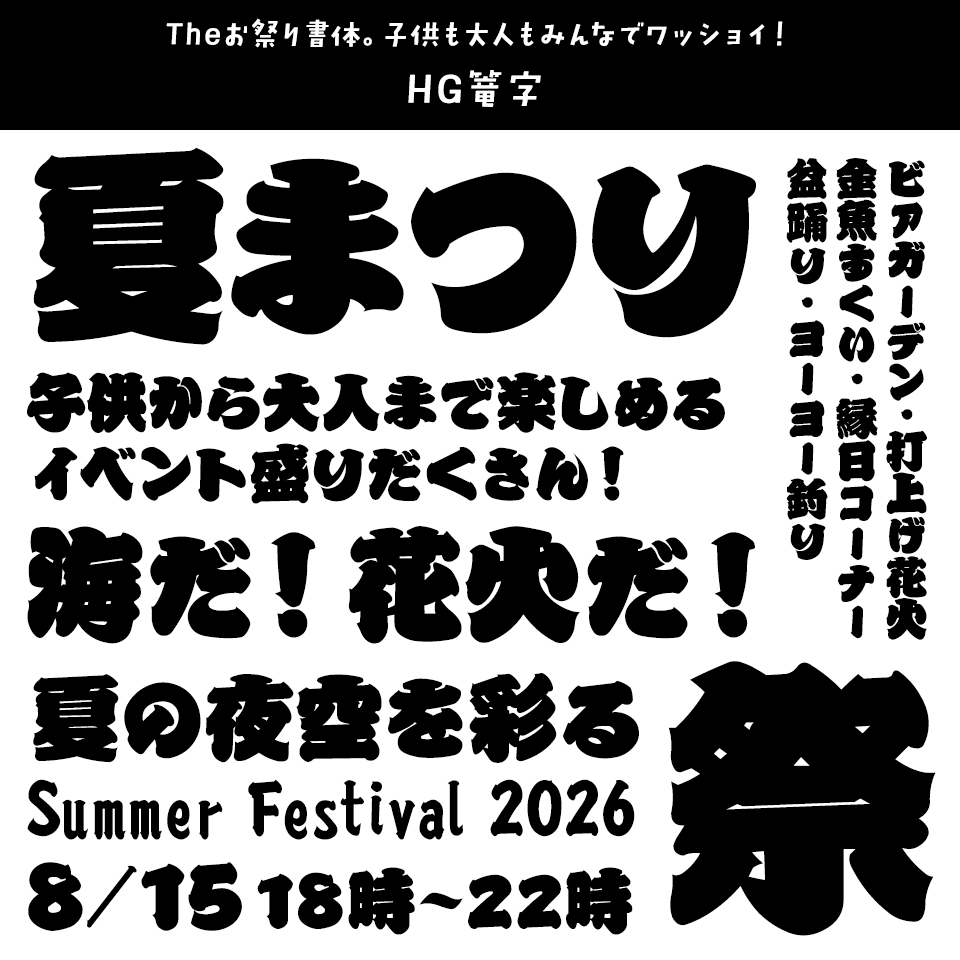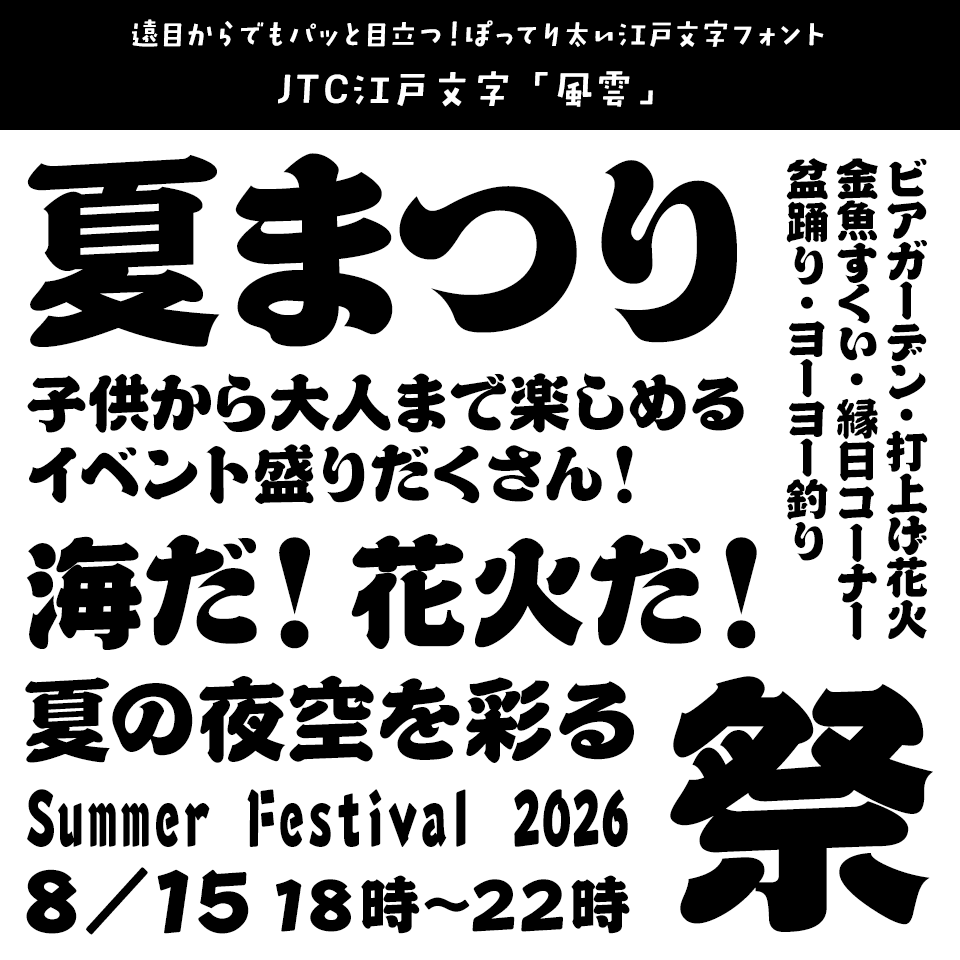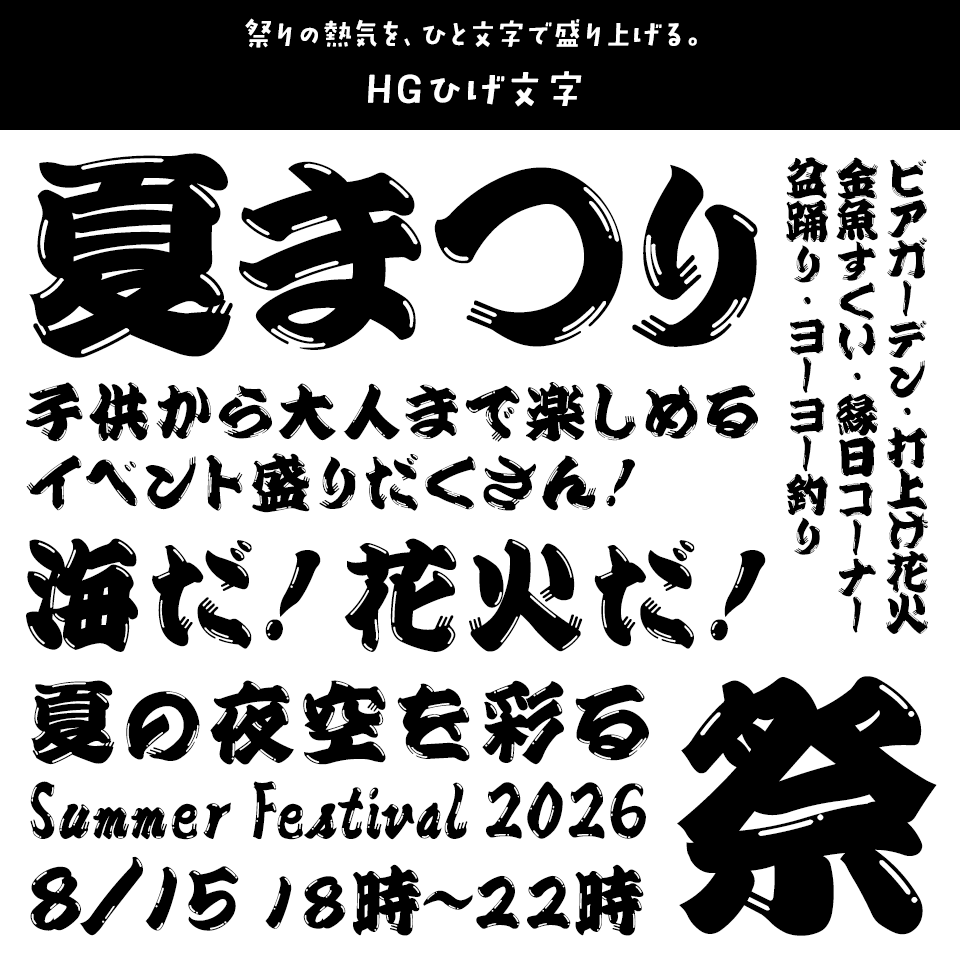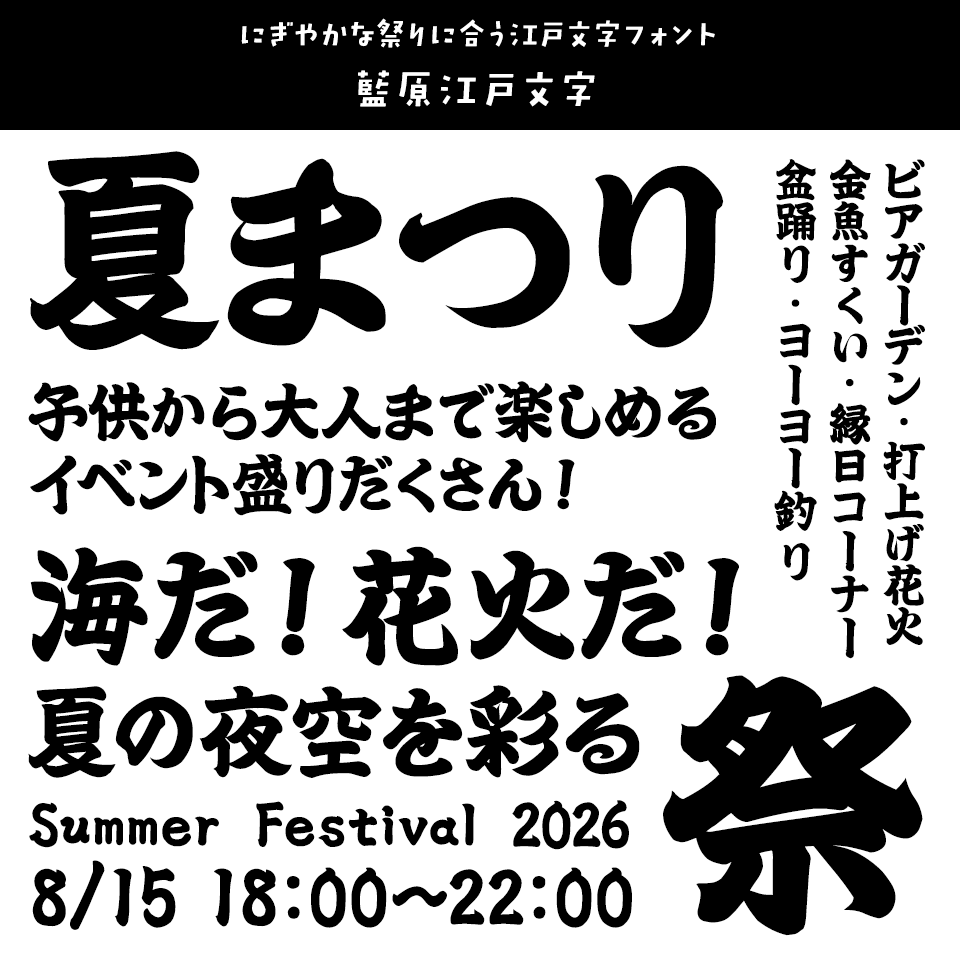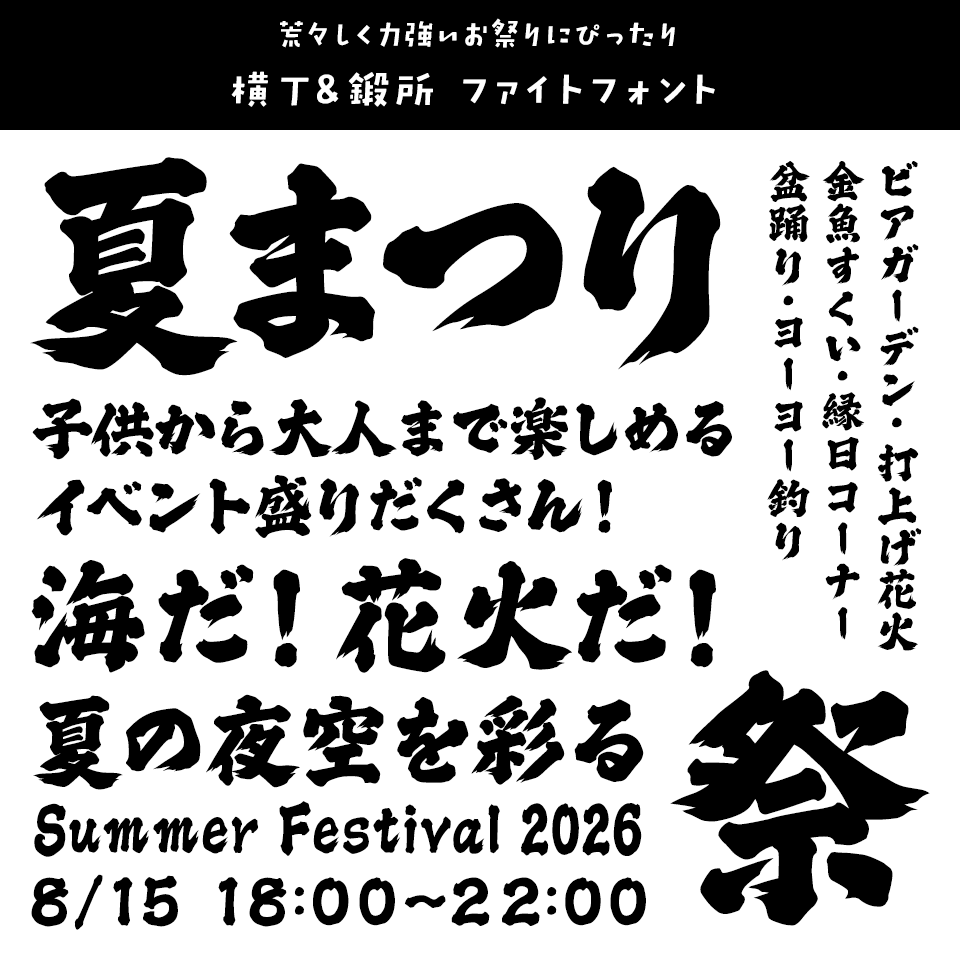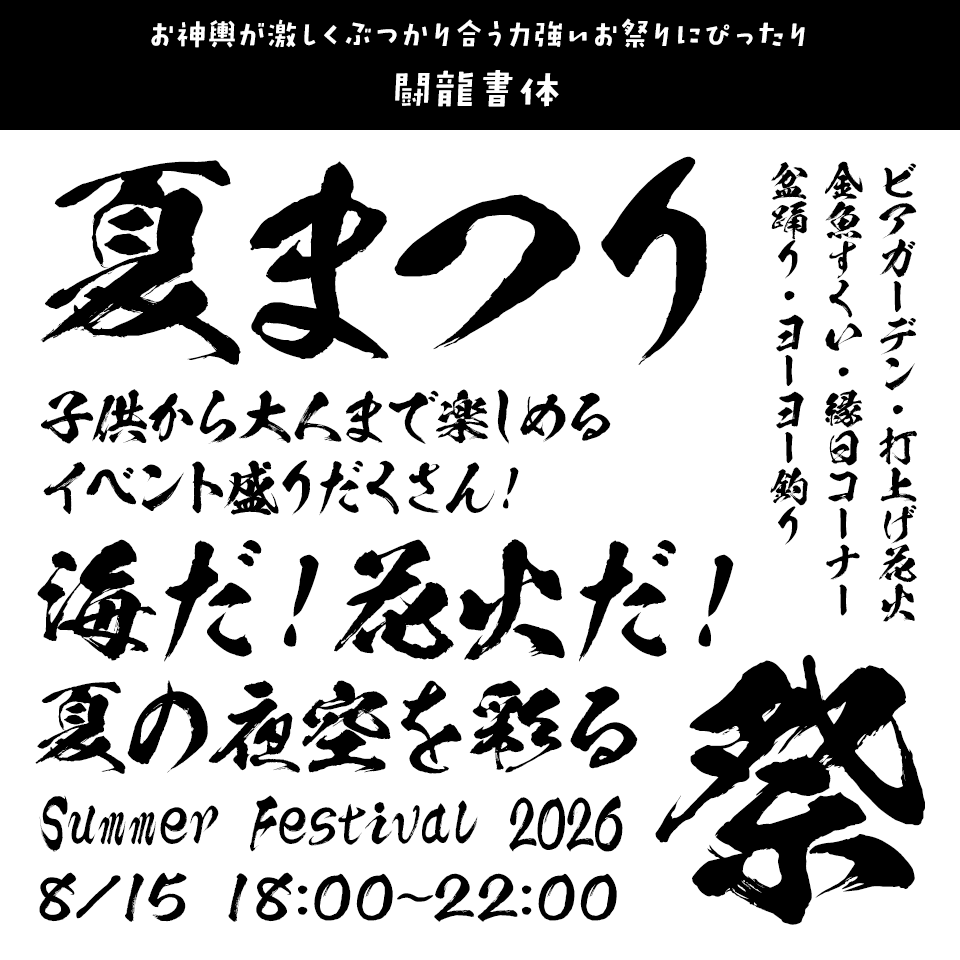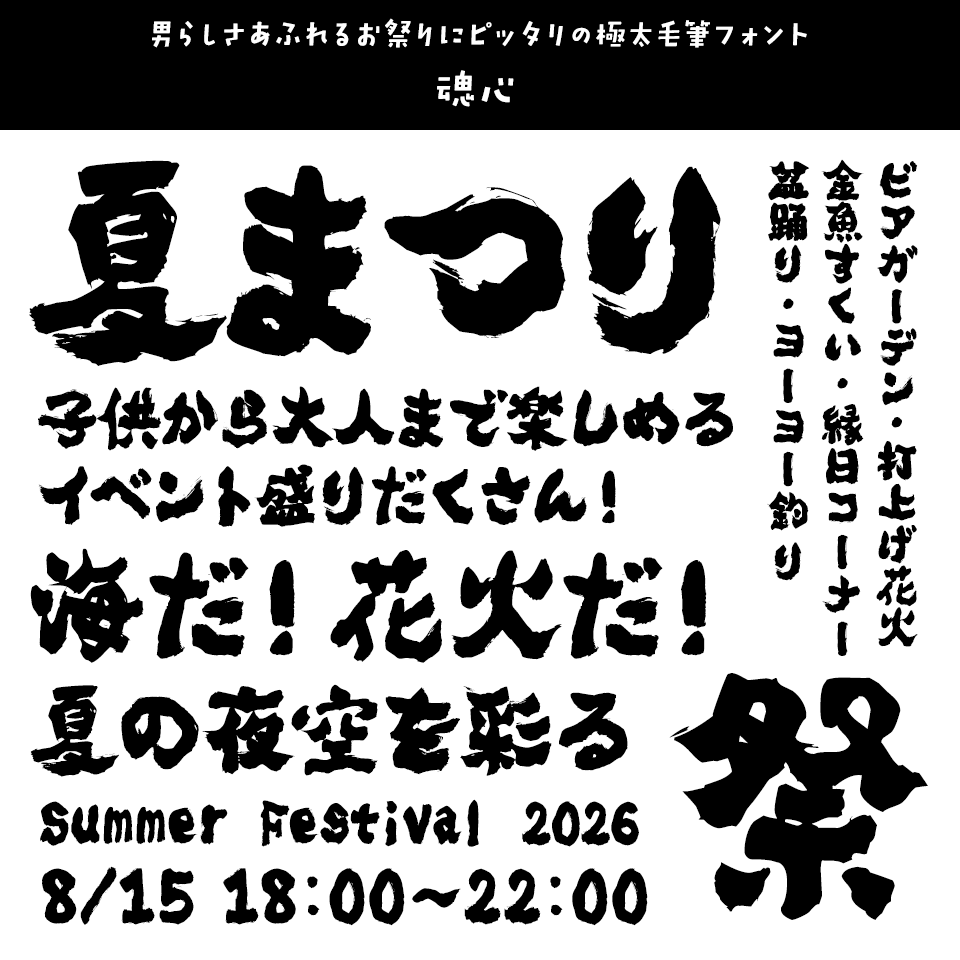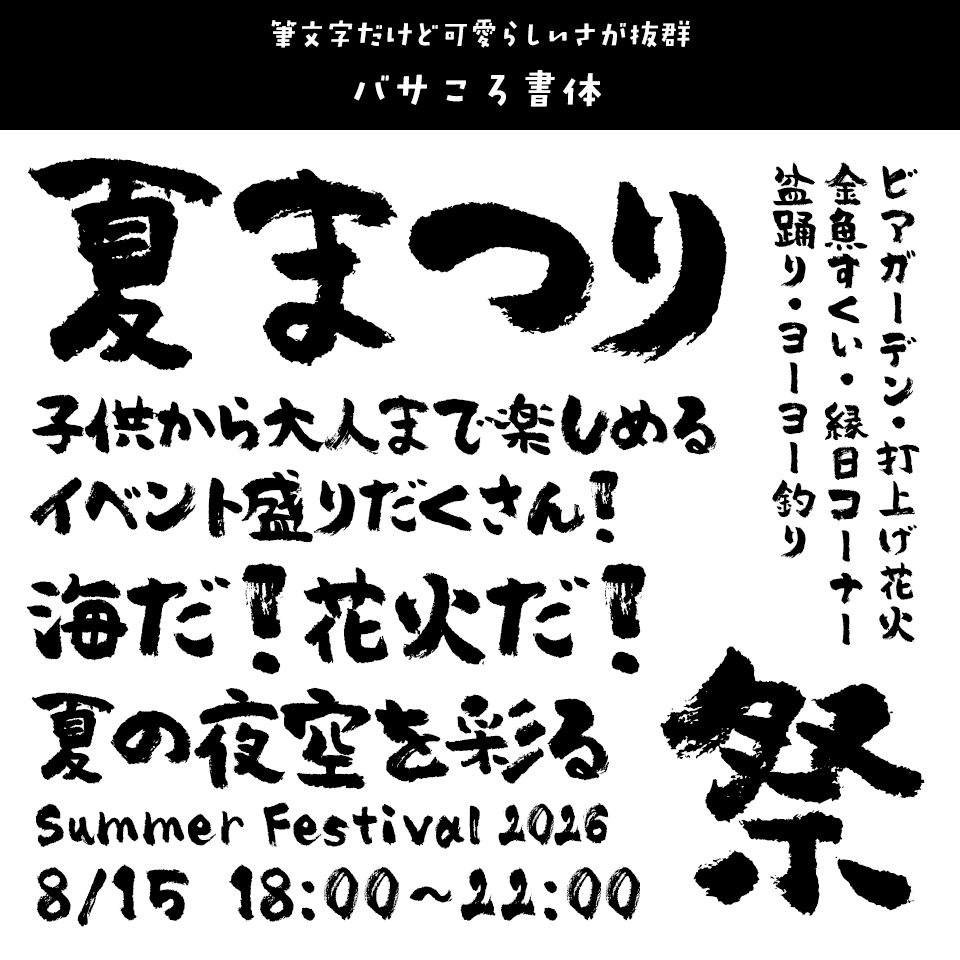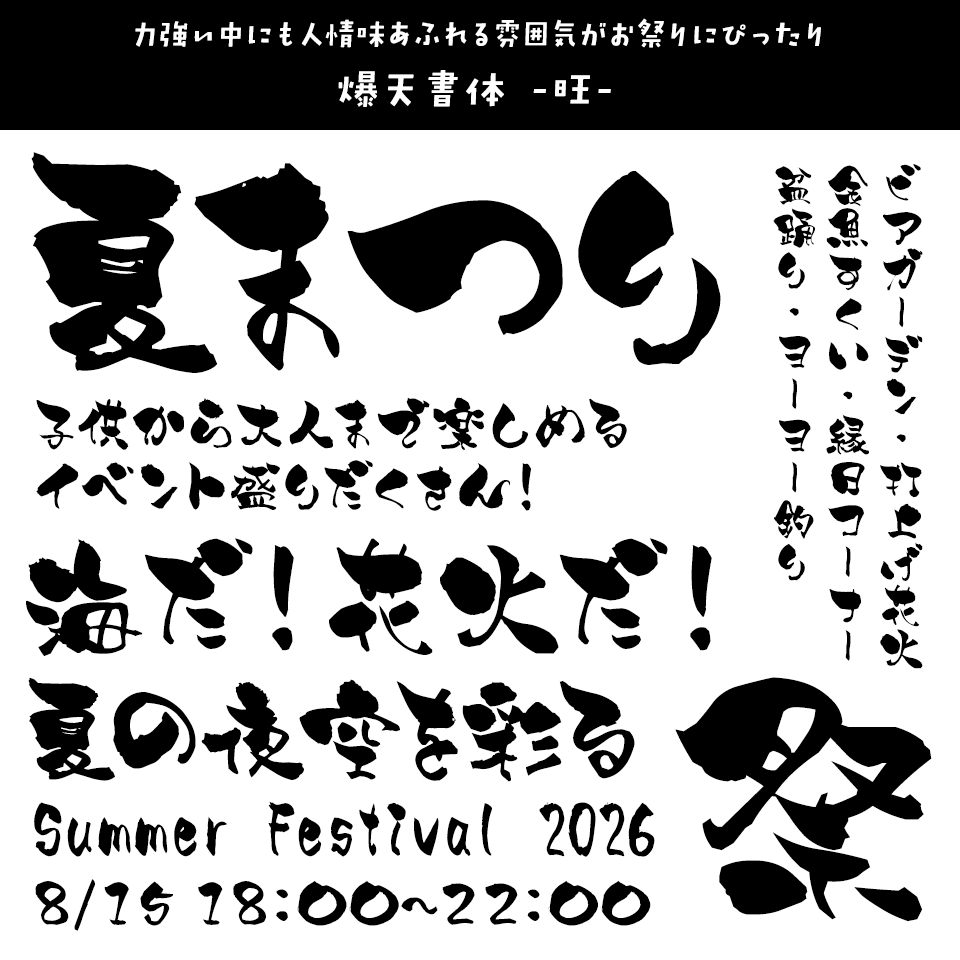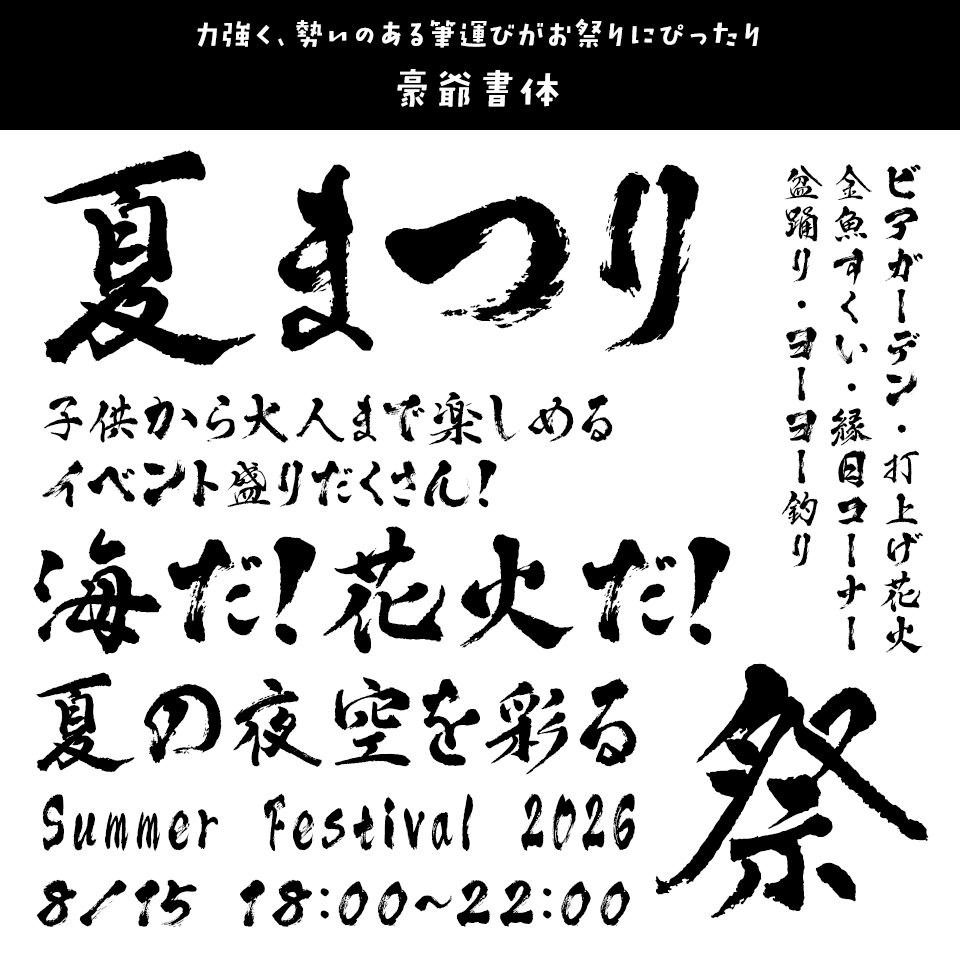
「祭り」に合うフォントをスタッフが選びました
「祭り」に合うフォント HG篭字
Theお祭り書体。子供も大人もみんなでワッショイ!
「祭り」に合うフォント HG篭字
鉢巻のような太さと、踊りをイメージさせるような動きのあるデザインです。出店にも使える読みやすいフォントです。
「祭り」に合うフォント JTC江戸文字「風雲」
遠目からでもパッと目立つ!ぽってり太い江戸文字フォント
「祭り」に合うフォント JTC江戸文字「風雲」
どっしりとした太さと親しみやすさを兼ね備えた定番の江戸文字フォント。屋台のメニューや縁日のPOP、提灯の文字など、遠くからでもパッと目を引く和風デザインに最適です。プライスカードに便利な外字も入っていて実用性も抜群です。
「祭り」に合うフォント HGひげ文字
祭りの熱気を、ひと文字で盛り上げる。
「祭り」に合うフォント HGひげ文字
文字の端にあしらわれた力強い「ひげ」が、祭りの熱気や勢いを演出する江戸文字フォント。のぼりや法被、屋台のメニュー、縁日のポスターなど、目を引く和風デザインに使えます。
「祭り」に合うフォント 藍原江戸文字
にぎやかな祭りに合う江戸文字フォント
「祭り」に合うフォント 藍原江戸文字
江戸っぽさ、日本っぽさを出したいとき、力強さが欲しいときなどにお勧めのフォント。千社札などに使われる千社文字を参考に作成しています。比較的読みやすく、動画のサムネイルやバナー、目を引きたい広告などに向いています。
「祭り」に合うフォント 横丁&鍛所 ファイトフォント
荒々しく力強いお祭りにぴったり
「祭り」に合うフォント 横丁&鍛所 ファイトフォント
勢いのあるはらいが特徴的な極太の毛筆書体で、荒々しく力強い印象を持っています。タイトルや見出し、ロゴなどにおすすめです。通常のフォント「横丁フォント」と、各エレメントを分解可能な「鍛所フォント」を同梱しています。
「祭り」に合うフォント 闘龍書体
お神輿が激しくぶつかり合う力強いお祭りにぴったり
「祭り」に合うフォント 闘龍書体
闘争心にあふれ、力がありあまった若い龍が、空を舞うさまをイメージした毛筆書体です。力強さ、荒々しさを持ちながらも、堂々と伸び渡る文字が、龍というにふさわしい、雄大なイメージを感じさせます。
「祭り」に合うフォント 魂心
男らしさあふれるお祭りにピッタリの極太毛筆フォント
「祭り」に合うフォント 魂心
『魂心』は、全身全霊、渾身の力を込めて書かれた魂の極太書体。
「祭り」に合うフォント バサころ書体
筆文字だけど可愛らしいさが抜群
「祭り」に合うフォント バサころ書体
よくある筆文字とは一味違ったデザイン性がある書体。ごろっとした丸さが見出しにはピッタリです。
「祭り」に合うフォント 爆天書体 -旺-
力強い中にも人情味あふれる雰囲気がお祭りにぴったり
「祭り」に合うフォント 爆天書体 -旺-
筆文字職人・墨人爆天が描いた毛筆書体。豪快な筆致でありながら、温もりと優しさを有した人情味ある書体に創り上げています。
「祭り」に合うフォント 豪爺書体
力強く、勢いのある筆運びがお祭りにぴったり
「祭り」に合うフォント 豪爺書体
勢いがよくばっさりとした力強さ、筆ならではの豪快さをアピールできる筆文字フォントです。大人気の『バサころ』書体の女流書家、恵彩院花梢の書体。
「祭り」に合うフォント 忍者
ダイナミックさと神秘性を持ち合わせたお祭りにぴったり
「祭り」に合うフォント 忍者
ダイナミックな動きをもち、豪快で鋭く、まさに忍者という言葉にふさわしい書体です。
「祭り」に合うフォント しょかきうたげ
祭と宴にぴったりな毛筆書体
「祭り」に合うフォント しょかきうたげ
居酒屋風フォント!居酒屋のメニュー風の字をイメージして作ったフォントです。すべて手書きの字を元に作られており、印刷で簡単に手書き風メニューを作ることができます。
「祭り」に合うフォント 筆技名人フォント 憩楽体(MNT憩楽体)
ポップと和が共存する楽しい丸文字毛筆フォント
「祭り」に合うフォント 筆技名人フォント 憩楽体(MNT憩楽体)
商品パッケージや居酒屋のメニューなど、食品関係を中心に、幅広いジャンルに使いやすいポップなイメージの毛筆フォント。
「祭り」に合うフォント ネオ勘
伝統の力強さを、現代的な祭りデザインに。
「祭り」に合うフォント ネオ勘
勘亭流らしい力強さを残しながら、丸みを抑えたシャープなデザインが特徴の書体。祭りのポスターや法被、のぼり、イベントタイトルなど、和の雰囲気を現代的でスタイリッシュに演出したい場面におすすめです。
「祭り」に合うフォント パンダベーカリー
お祭りや縁日のにぎやかな雰囲気にぴったりな手書きフォント
「祭り」に合うフォント パンダベーカリー
太くて読みやすく、手書きならではの温もりとかわいらしさが魅力の「パンダベーカリー」。りんご飴やわたあめ、かき氷などの屋台POPやメニュー、お祭りのチラシやイベントバナーにもぴったりです。
「祭り」に合うフォント モトヤゴチカ8
昭和の雰囲気のあるお祭りにぴったり
「祭り」に合うフォント モトヤゴチカ8
ゴシック体をベースとして横線やハライに筆文字の勢いを表現することで、躍動感とチカラ強さを感じさせる書体です。
「祭り」に合うフォント JTC神楽
わっしょい!!「祭り」と「炎上」は違うんでぇい!!
「祭り」に合うフォント JTC神楽
「炎上」は非難や批判が集中して大騒ぎになること。対する「祭り」は、ただ盛り上がってお祭り騒ぎになること。そんなポジティブな「祭り」に合うフォントは、祭りの華やぎ、お囃子のリズム、モダンとレトロの共存した「JTC神楽」ラッセラー!
「祭り」に合うフォント やんちゃポップ じたばた
お祭りの楽しさを感じさせるユニークなフォント
「祭り」に合うフォント やんちゃポップ じたばた
元気いっぱいの筆致とランダムな文字配置が特徴のお祭りにぴったりのフォントでポスターやチラシ、屋台の看板などに活用すれば、にぎやかで楽しい雰囲気を演出できます。
「祭り」に合うフォント かるた-BOLD